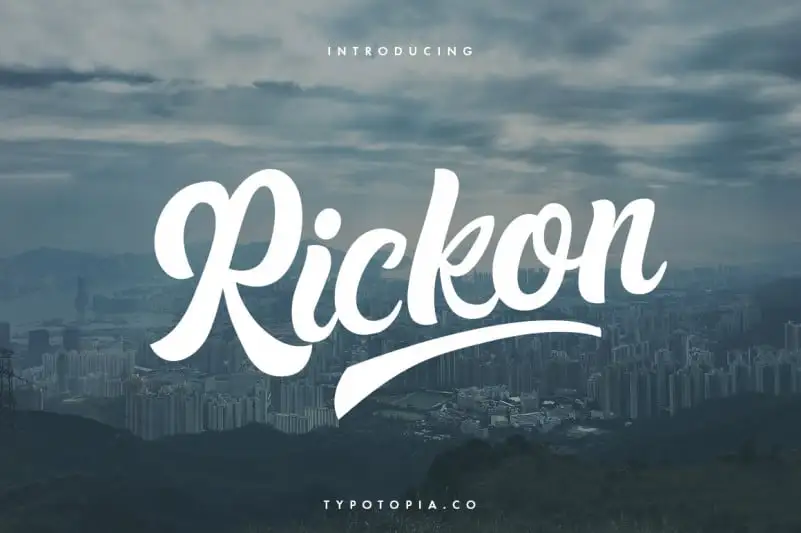
Rickon Script Font – Download Grátis
A Rickon Script Font é uma elegante tipografia feita à mão que encanta os olhos por sua versatilidade única. Esta fonte é perfeita para quem procura algo refinado e autêntico para seus projetos de design, especialmente em cartões de convite de casamento, arte para materiais de escrita, postagens impactantes nas redes sociais, e muito mais. Ideal para aquela decoração especial que deseja chamar a atenção dos convidados, Rickon Script é uma escolha segura para qualquer projeto onde você quer transmitir elegância e delicadeza através do design gráfico.